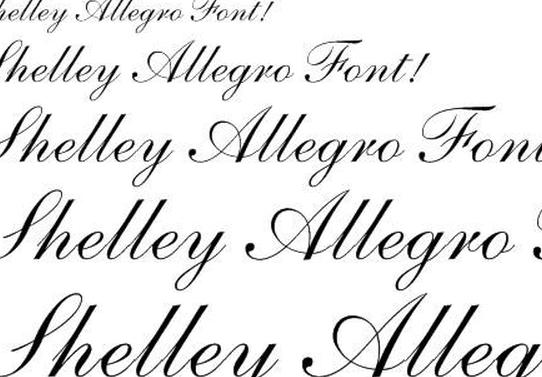
Как и его родственный шрифт Shelley Volante , было бы неплохо найти веб-сайт с бесплатными шрифтами Shelley Allegro. Вся семья Shelley — отличный инструмент для придания элегантности сайту; однако, как и многие хорошие вещи, его трудно получить бесплатно.
Итак, где вы можете получить Шелли Аллегро?
Потратив время на оплату шрифта, вы можете быть уверены, что выбрали правильный. Дополнительные инструменты, такие как «водопад» (на фото справа), позволяют увидеть, как шрифт преобразуется в разные размеры.
Правильный шрифт, правильный размер, правильное сообщение
Тестирование шрифта — важная часть выбора правильного. Shelley Allegro — очень изогнутый шрифт с засечками и большим количеством росчерков. Это может быть неподходящий шрифт для основного текста или идеальный заголовок. Вот некоторые элементы, которые следует учитывать:
- Какие еще шрифты используются в документе? Дополняют ли они Shelley Allegro (т. е. без засечек на засечки)?
- Ваше сообщение можно прочитать с помощью Shelley Allegro? Именно здесь инструменты «водопад» и «образец текста» на веб-сайте являются ключевыми.
- Вам нужны полужирный шрифт, контуры или другие эффекты шрифта? Как насчет специальных символов ? Убедитесь, что они включены в пакет шрифтов, который вы покупаете. Пакеты шрифтов, такие как на сайте Find Fonts , содержат полный спектр специальных символов).
Где использовать Шелли Аллегро
Мэтью Картер, дизайнер, создавший все три варианта Shelley в 1972 году, хотел, чтобы завивающиеся линии придавали элегантный формальный вид. Он сделал все строчные буквы одинаковыми для всех трех и просто поменял заглавные в каждой. Когда он напечатан, он создает иллюзию прекрасного каллиграфического почерка и полезен для таких вещей, как приглашения на необычный ужин, реклама предметов роскоши или вообще попытка передать изящное сообщение высокого класса.